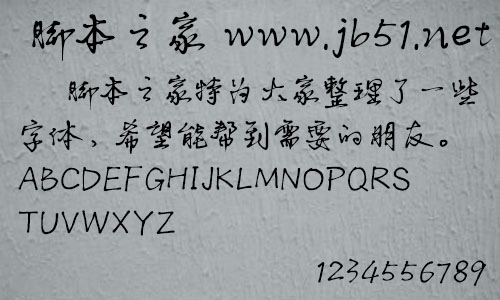
默陌隨想體細(xì)是一款中文手寫(xiě)字體,這款字體的筆觸較為纖細(xì),字體清晰明朗,適合應(yīng)用于藝術(shù)設(shè)計(jì)、平面宣傳設(shè)計(jì)、網(wǎng)頁(yè)設(shè)計(jì),書(shū)法字帖等領(lǐng)域,需要的朋友可以前來(lái)本站下載。